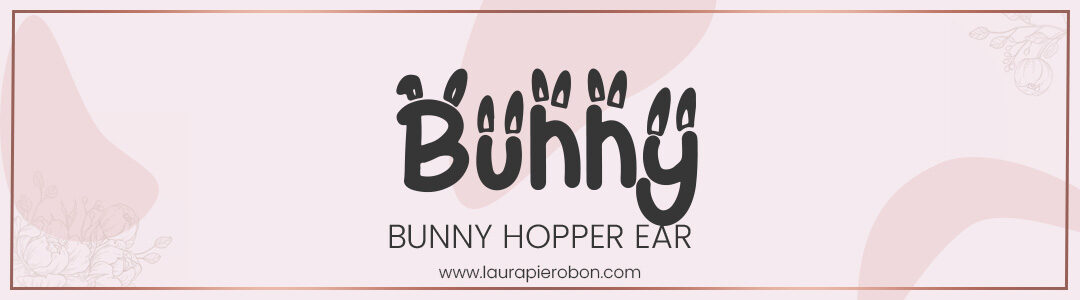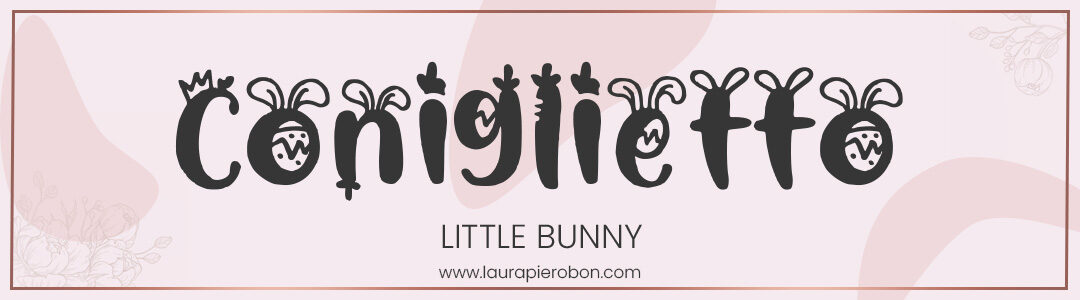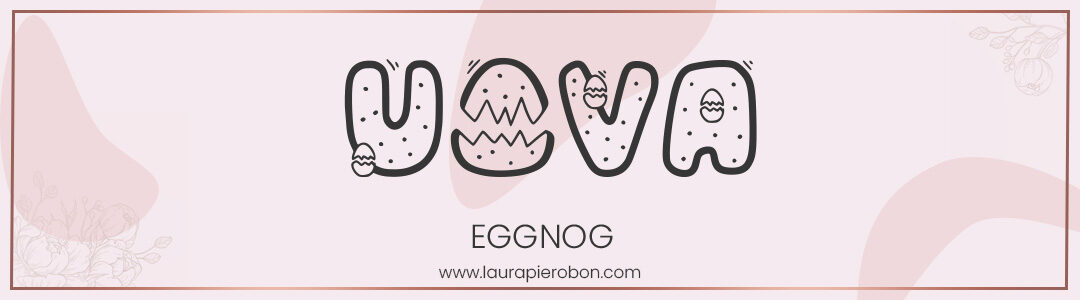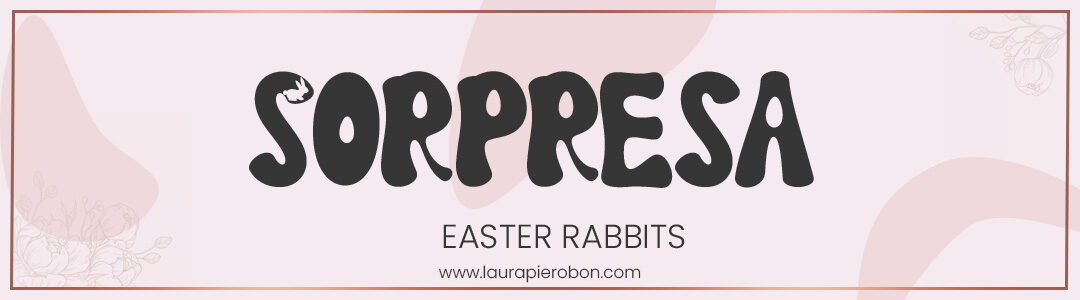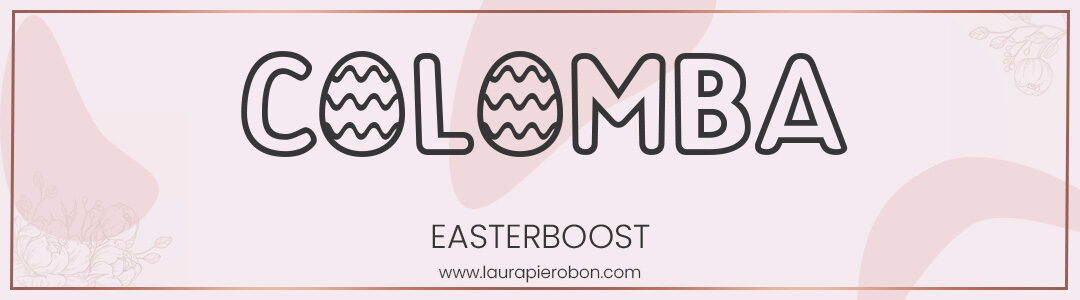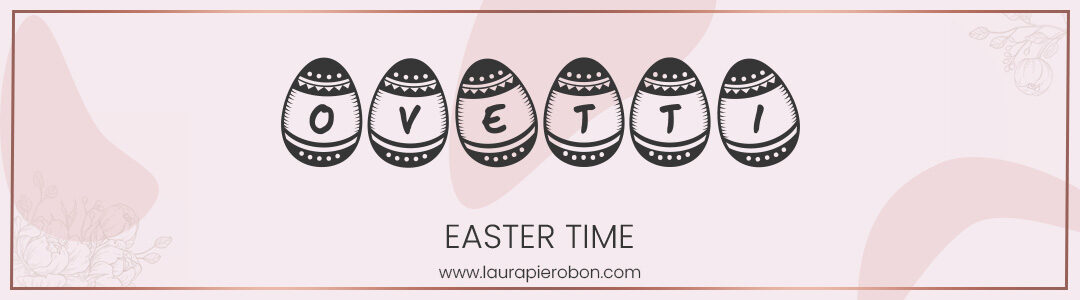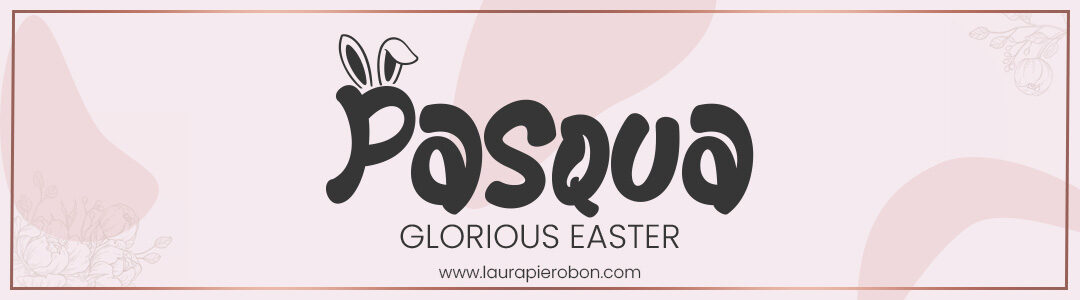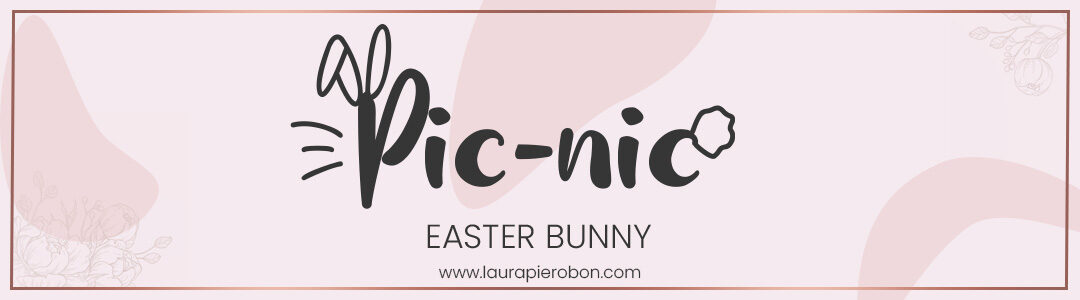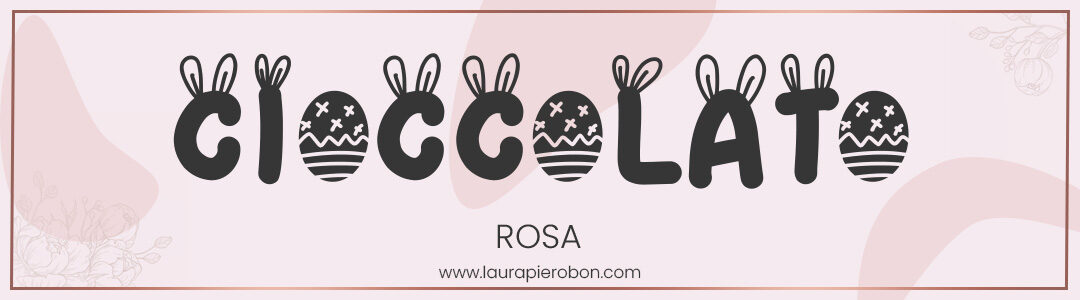
Hai mai pensato di rendere le tue creazioni pasquali ancora più speciali con dei font unici?
La Pasqua è il momento della rinascita, della luce e dei nuovi inizi — un’occasione perfetta per portare nei tuoi progetti un tocco di freschezza e colore.
Che tu stia realizzando biglietti d’auguri, inviti digitali, grafiche per i social o materiali per il tuo negozio online, scegliere il font giusto può davvero fare la differenza. Un carattere dal tratto morbido e allegro può trasmettere subito leggerezza, dolcezza e positività — le stesse emozioni che associamo alla primavera e alle feste pasquali.
Per questo ho raccolto una selezione di 10 font creativi e gratuiti perfetti per i tuoi progetti di Pasqua: troverai calligrafie morbide, scritte giocose e lettering decorativi che richiamano fiori, coniglietti e uova colorate. In poche parole, tutto ciò che serve per aggiungere un pizzico di magia primaverile alle tue creazioni 💐
🐰 10 font creativi da usare per la Pasqua
Bunny Hopper Ear – Un font simpatico e vivace, con piccoli coniglietti che spuntano dalle lettere. Ideale per grafiche allegre o card per bambini.
Little Bunny – Morbido e dolce come un batuffolo di cotone: perfetto per testi brevi, biglietti e loghi a tema pasquale.
Eggnog – Arrotondato e goloso, ricorda le uova di cioccolato. Ottimo per progetti allegri e colorati.
Easter Rabbits – Un font decorativo con dettagli illustrati che raffigurano coniglietti e motivi primaverili. Ideale per titoli o copertine creative.
Easterboost – Linee morbide e leggere che trasmettono energia e positività. Perfetto per post social o grafiche moderne.
Easter Time – Un font dal sapore vintage ma giocoso, che si abbina bene a colori pastello e grafiche delicate.
Glorious Easter – Elegante e decorativo, ideale per progetti più raffinati o per biglietti d’auguri con un tocco poetico.
Easter Bunny – Allegro e versatile, adatto a tantissimi usi: da titoli di blog a grafiche per piccoli shop.
Rosa – Calligrafico e romantico, perfetto se vuoi un effetto delicato e femminile nelle tue creazioni pasquali.
Teloraster – Un display font originale e contemporaneo, con curve armoniose che donano movimento e vivacità.